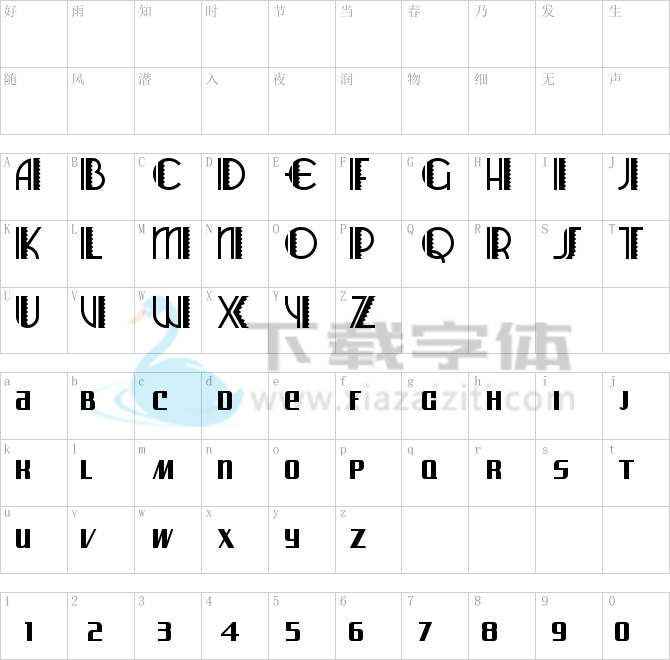
Arizona Airways NF.ttf字体下载,这款字体结构工整、笔画清晰,兼顾美观与易读性,适用于标题、正文、海报、包装、LOGO 等多种场景。字形优雅稳定,风格百搭耐看,适配日常排版与创意设计,让文字呈现更舒适、更具质感。Arizona Airways NF.ttf字体下载一笔一画,皆是细节,以均衡的比例、流畅的线条打造舒适视觉体验,字形端正大气,风格简约现代。无论是商业设计、品牌宣传还是日常排版,都能轻松驾驭,让文字更有格调与力量。Arizona Airways NF.ttf字体下载字体下载。